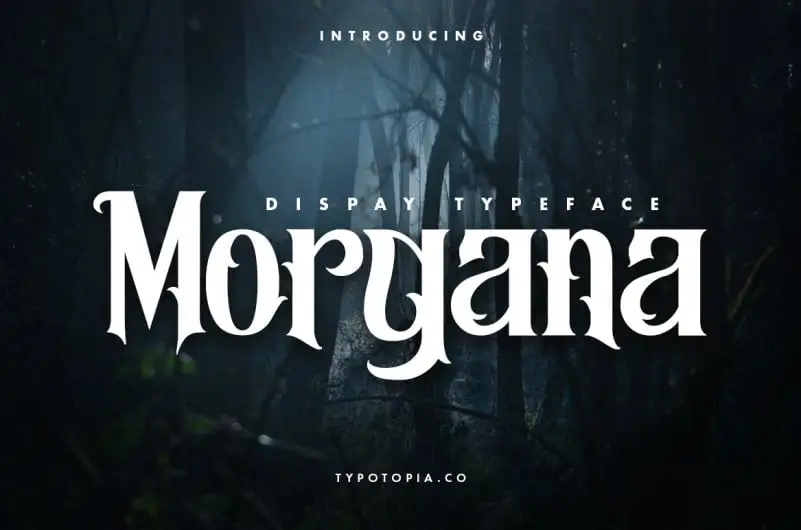
Morgana Display Font – Download Grátis
Descubra a Morgana Display Font, uma nova adição à família dos carimbos digitais da typotopia. Inspirada na elegância das letras do passado, essa fonte moderna mantém sua personalidade única e sofisticada. Com um ar natural que captura a essência de uma era antiga, Morgana Display Font traz leveza e facilidade à sua tipografia, tornando-a perfeita para qualquer aplicação que exija elegância e modernidade. Ideal tanto para design gráfico profissional quanto para criações artísticas criativas, essa fonte oferece a combinação perfeita de sofisticação e contemporaneidade. Não deixe de explorar a Morgana Display Font em sua próxima projeto visual.